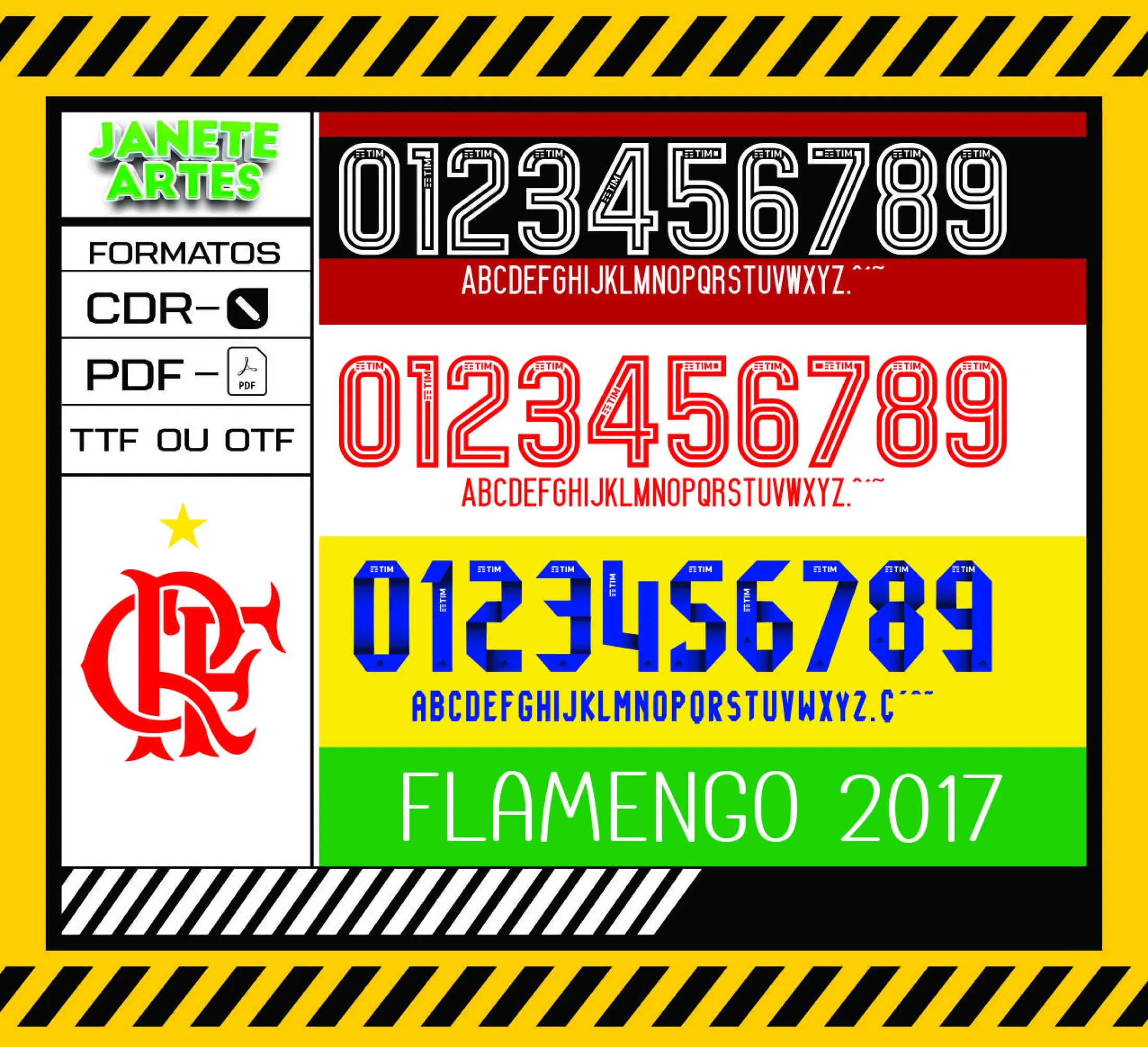
Fonte de Time Tipografia Flamengo 2017
• Design da fonte oficial da tipografia usada pelo Flamengo em 2017 para personalizar camisas, blusas e camisetas.
• Combine a fonte com cores clássicas do Flamengo, como preto, vermelho e branco para maior impacto visual.